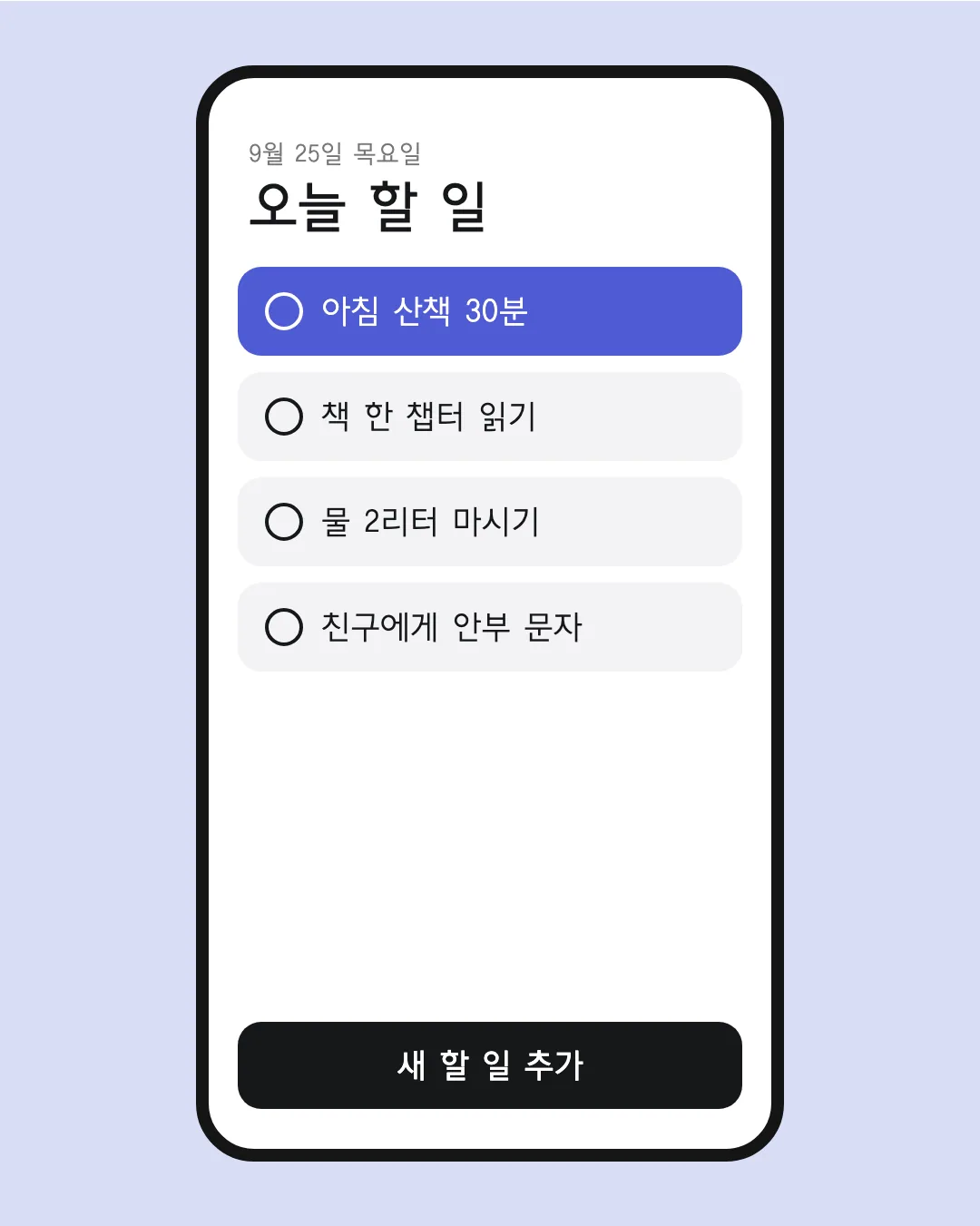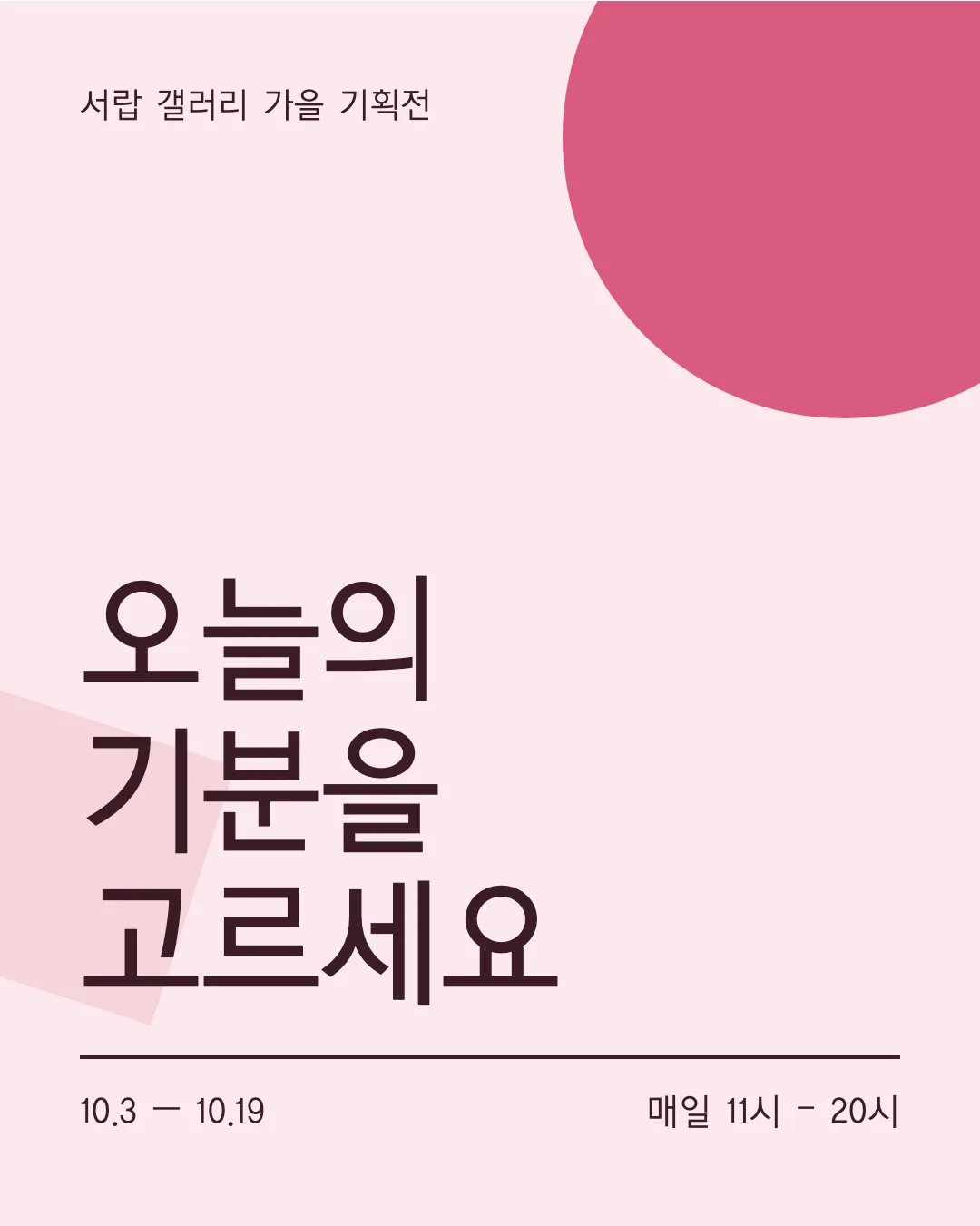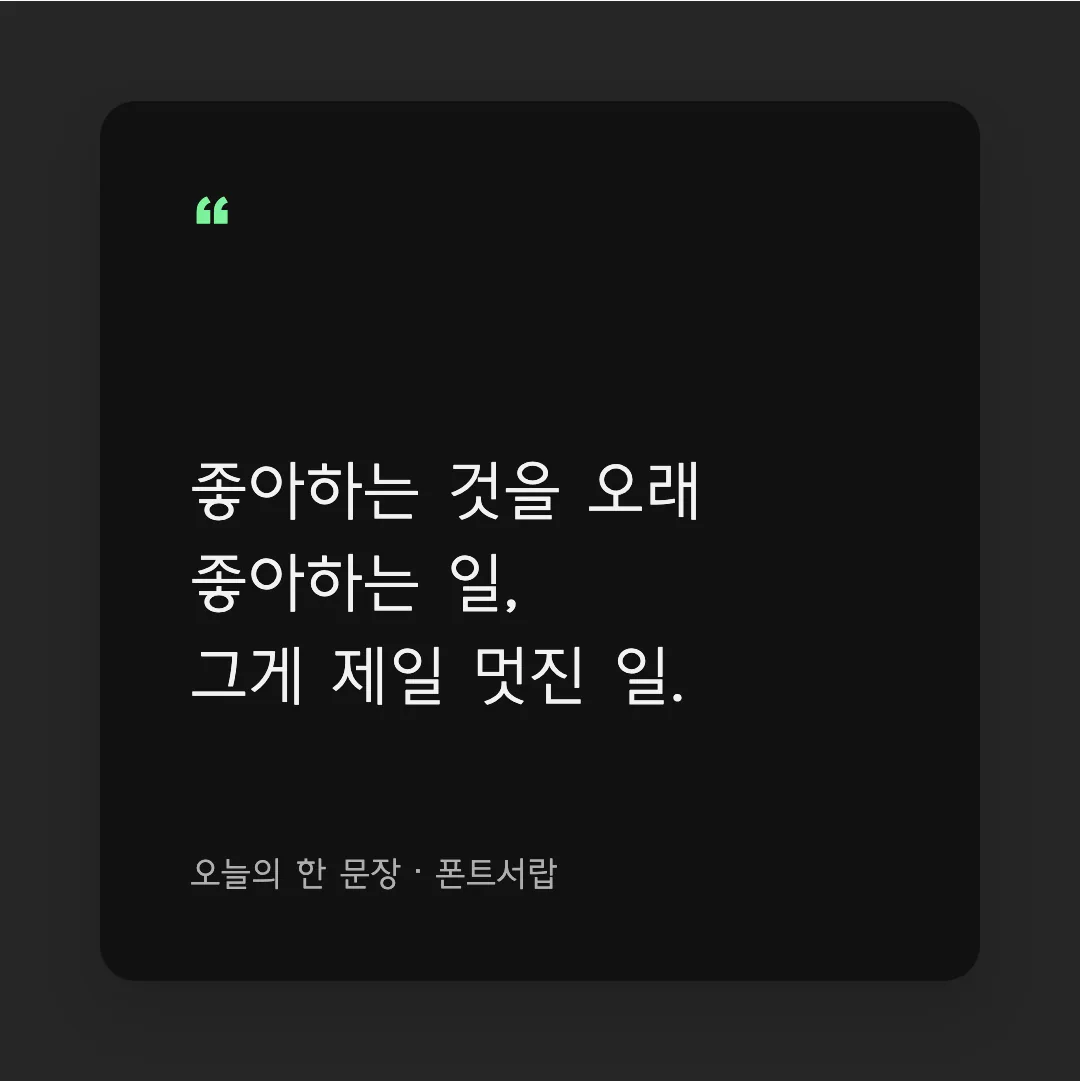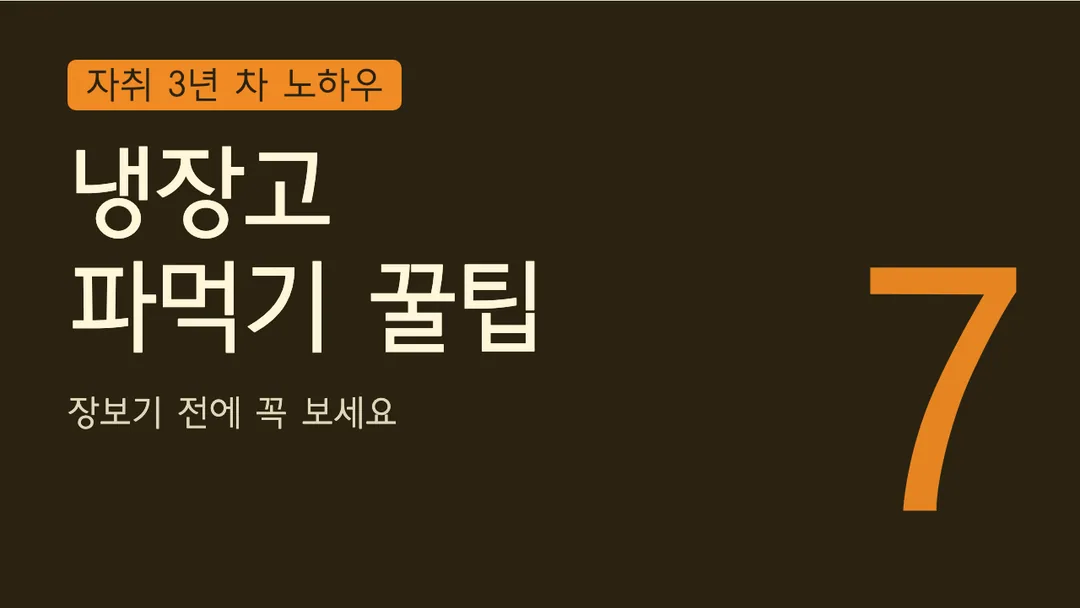
학교안심 산뜻돋움
Hakgyoansim Santteutdotumthic
- 제작
- 한국교육학술정보원 (KERIS)
- 형태
- 고딕
한국교육학술정보원(KERIS)이 학교에서 저작권 걱정 없이 쓰도록 배포하는 학교안심 폰트 중 고딕입니다. 수업 자료와 안내문에 두루 쓰기 좋습니다.
학교안심 산뜻돋움로 직접 만들어 본 디자인 예시예요. 이미지를 누르면 크게 볼 수 있어요.